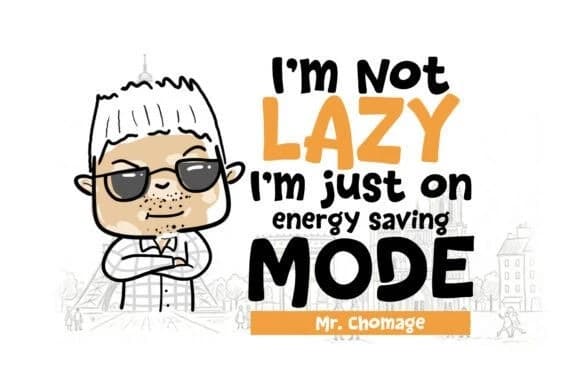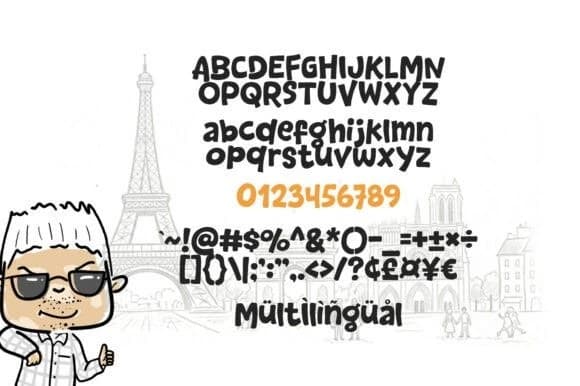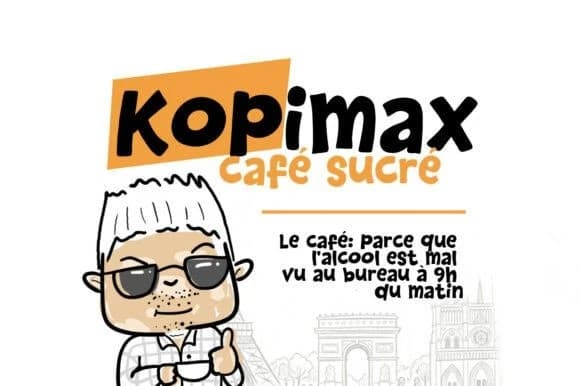
Chomage Görüntü Yazı Tipi
Chomage Display Font, neşeli, kalın ve eğlenceli bir display fontudur. Bu yazı tipi, kalın ve organik harf biçimlerine sahip olup, yumuşak, yuvarlak kenarlara ve ritmik, hafif düzensiz bir taban hattına sahiptir; bu, bir marker eskizinin spontane hissini taklit eder.
Chomage Display Font, keyifli derecede kalın ve oyunbaz bir başlık yazı tipidir. Bu yazı tipi, kalın ve organik harf biçimlerine sahip, yumuşak, yuvarlak kenarlı ve ritmik, hafif düzensiz bir temel hattına sahip olup, marker çiziminin spontane hissini taklit eder.